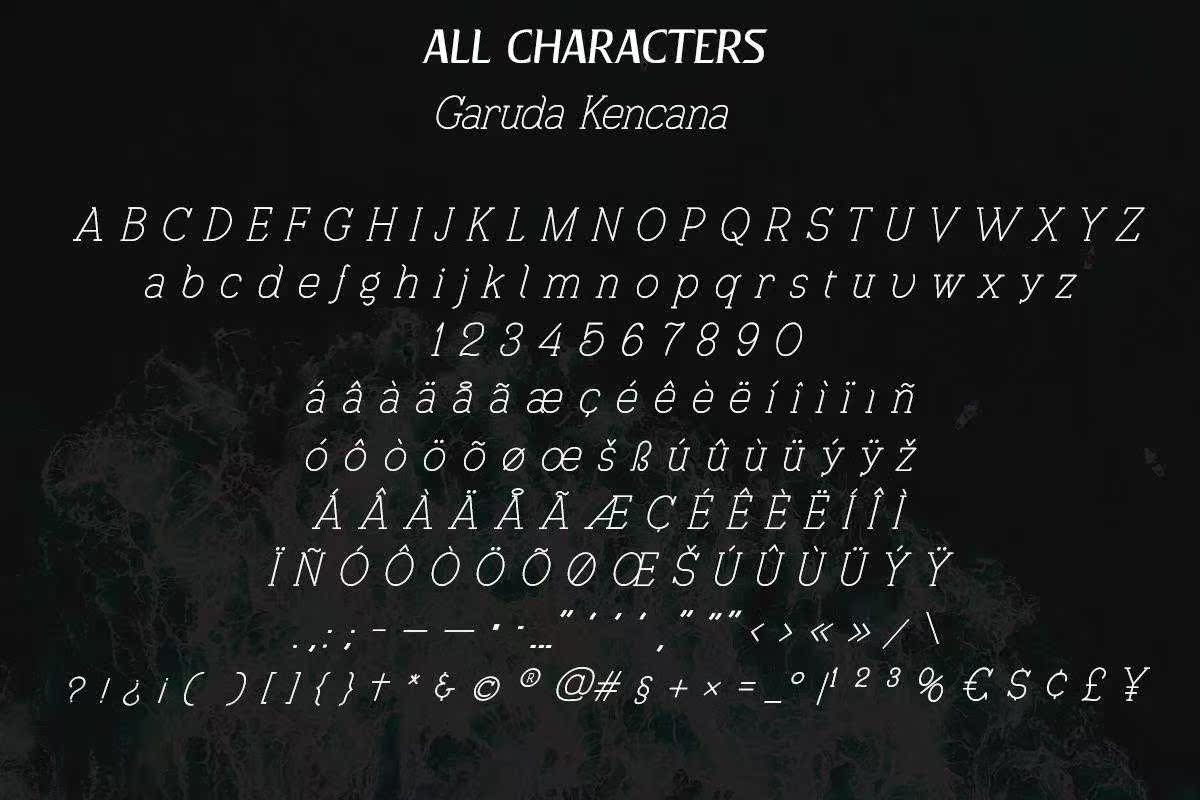
Hellofriend.Garudakencanafont是一个现代的字体家族,它的设计是指衬线的样式。这种字体的笔划对比度相对较低,其鲜明的方形特征与强调的商业性相似。它是由Mevstudio设计的。与它的各种替代品相结合,你可以根据自己的设计创造出独一无二的风格。在博客(子)标题、品牌和其他方面都有相当高的知名度。Hellofriend。Garudakencanafont是一个现代字体家族,其设计风格是指衬线风格。这种字体的笔画对比度相对较低,这是由Mevstudio设计的一款具有鲜明个性和强调商业性的简洁方格。它与各种可选方案相结合,可以让您的设计达到独一无二的效果。对日志、(子)标题、品牌和其他内容都有同等的评价。